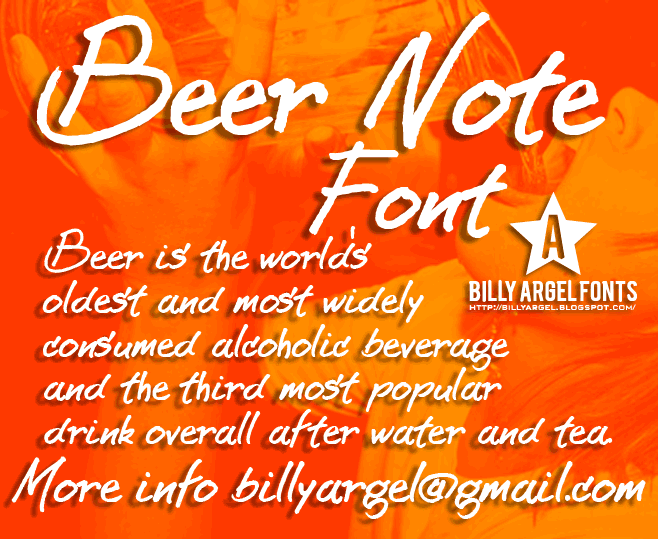
BEER NOTE Font
A fonte ‘BEER NOTE’ oferece uma experiência única e envolvente para aqueles que apreciam a arte do design gráfico. Desenvolvida pelo designer Hamilton, essa fonte tem um tom delicado e handwritten, perfeita para adicionar um toque pessoal aos designs. Seja ela usada em rótulos de cervejas, mensagens personalizadas ou até mesmo na criação de logos, a ‘BEER NOTE’ convida você à explorar suas nuances sutis e graciosas. Com uma aparência minimalista que transmite confiança, esta fonte é perfeita para quem procura algo que brinque com o formato humano do texto enquanto mantém sua elegância. Não só isso, mas seu design handwritten torna-a ideal para designers procurando um pouco de personalidade em seus projetos sem comprometer a legibilidade crucial. Instale ‘BEER NOTE’ e inspire-se na criatividade da arte da fonte!